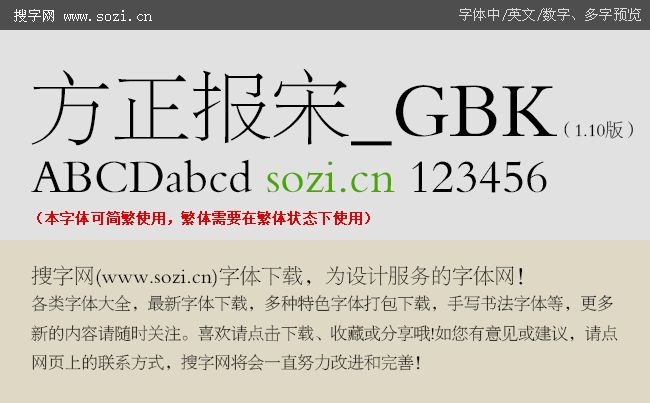
方正報(bào)宋_GBK
搜字網(wǎng)提供一款方正報(bào)宋_GBK中文字體下載,方正報(bào)宋是一款字形端莊的中文字體,該字體字體結(jié)構(gòu)端正、重心平穩(wěn)、美觀實(shí)用。GBK碼收錄字體更全,適合應(yīng)用于廣告設(shè)計(jì)、名片設(shè)計(jì)、包裝印刷、產(chǎn)品設(shè)計(jì)等應(yīng)用。